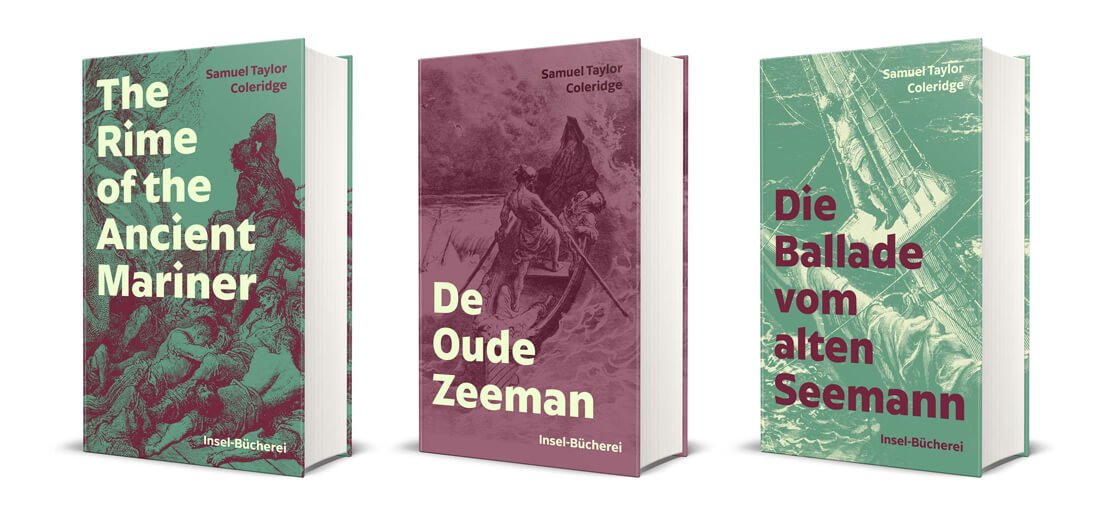
»Arpona Sans« von Felix Braden
Designer Felix Braden präsentiert die neue Schriftfamilie »Arpona Sans«. Die Serifenlose wurde von Edward Johnstons Schriftentwürfen für das Leitsystem der Londoner U-Bahn inspiriert.
Wie auch ihr serifenbetontes Pendant Arpona, ist sie eine Symbiose aus verschiedenen Designkonzepten. Durch das humanistische Konzept und die Sachlichkeit der klassizistischen Proportionen verbindet die Schriftart die Ästhetik einer geometrischen Sans mit entsprechender Lesbarkeit. »Arpona Sans« eignet sich somit für Editorial Design, Branding, App-Design, Webdesign etc. und lässt sich unter anderem im Fließtext an Bildschirm oder Handy verwenden.
Die Familie hat neun Schnitte (von »Thin« bis »Black«) sowie entsprechende Kursiven. Die Stile umfassen jeweils 588 Glyphen, die alle west-, ost- und mitteleuropäischen Sprachen unterstützen. Darunter befinden sich vier Ziffernsätze und verschiedene Währungssymbole.
Entwurfsprozess der »Arpona Sans«
»Als ich gerade die Arbeit an meiner Serifenschrift Arpona beendet hatte, beschloss ich, das Konzept als Sans zu testen und zeichnete ein paar Skizzen.«, so Felix Braden. »Das Ergebnis, das mir am besten gefiel, erinnerte mich an das Alphabet, das Edward Johnston für die Londoner U-Bahn zeichnete und das später von Eric Gill überarbeitet und als Gill Sans veröffentlicht wurde.«
Der Designer führt weiter aus: »Gill Sans war ein einflussreicher Vorläufer aller modernen Humanistischen Serifenlosen und ist auch für das Konzept der Geometrischen Serifenlosen von Bedeutung. Die Schrift ist auch heute noch in Gebrauch, aber man findet in vielen Buchstaben skurrile Details (z.B. der kalligrafische Einfluss bei „a“ und „R“, der rechte Winkel bei „p“ und „d“ oder die extreme Dynamik im Duktus) und leider war die Familie nie ein wirklich homogenes Design, genauso wenig wie die einzelnen Schnitte.«
»Wegen des individuellen Charakters der Schrift gefiel mir die Idee, Gill Sans neu und zeitgemäß zu interpretieren. Ich entschied mich, die Mischung der Konzepte beizubehalten und sogar noch mehr Komponenten hinzuzufügen, denn moderne Buchstabenproportionen sind durch ihre Regelmäßigkeit am Bildschirm besser zu lesen. Außerdem habe ich ungewöhnliche Details entfernt und in ein konsistentes Designsystem implementiert.«